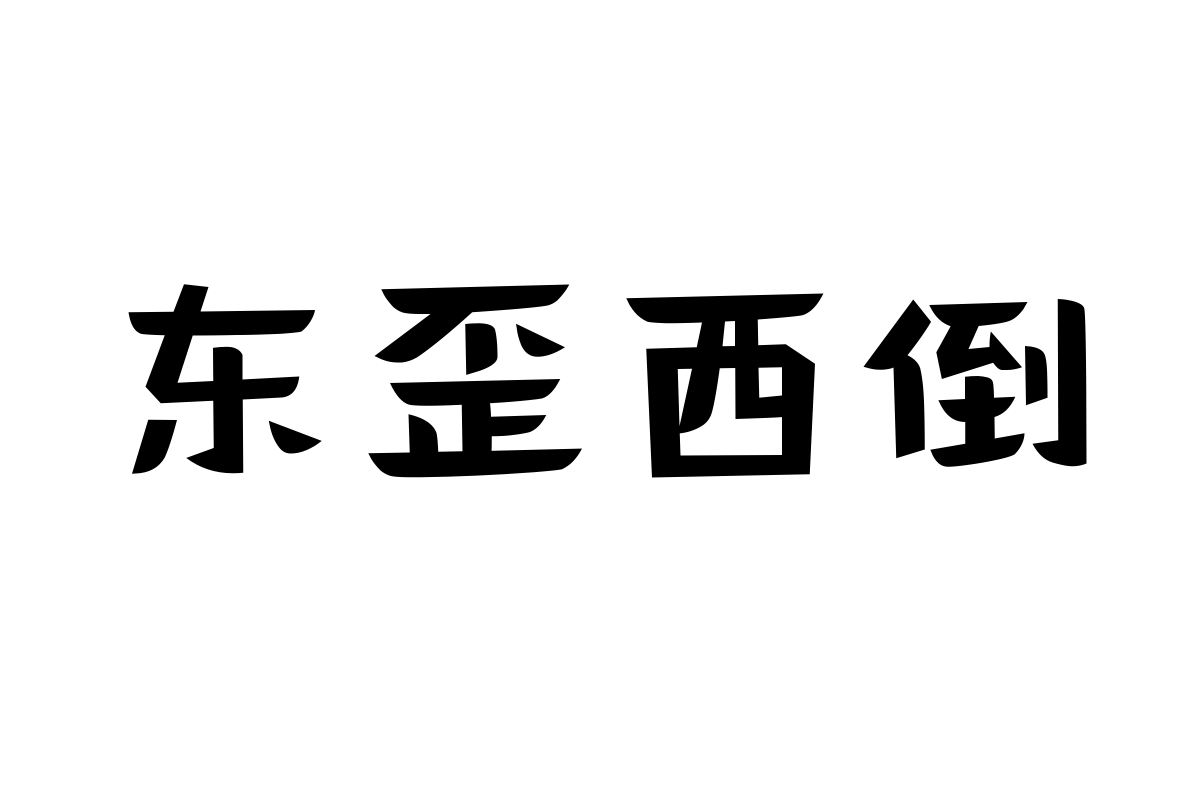
伊茶体是一种现代中文字体,由设计师张华设计。这种字体的特点是字形简洁、线条流畅、结构紧凑,适合用于各种商业、广告、包装等场合。
伊茶体的笔画粗细适中,既有传统的书法韵味,又不失现代感。它的每个字都经过精心设计,既有美感,又有实用性。此外,伊茶体还具有良好的可读性,无论是在小字号还是大字号下都能保持清晰易读。
总的来说,伊茶体是一款非常适合现代设计的字体,无论是在网页设计、平面设计还是包装设计中,都能发挥出其独特的魅力。